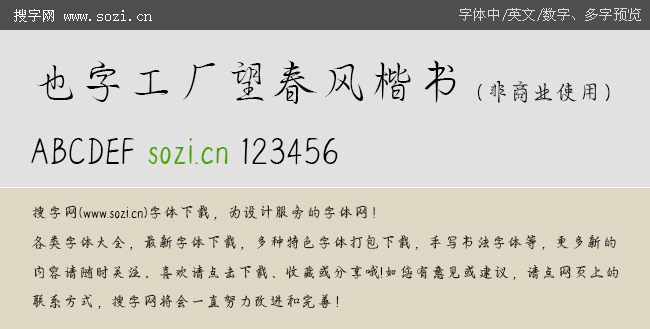
也字工廠望春風(fēng)楷書(shū)
搜字網(wǎng)給大家提供一款也字工廠望春風(fēng)楷書(shū)(非商業(yè)使用)中文字體下載,也字工廠望春風(fēng)楷書(shū)是一款手寫(xiě)字體,字體書(shū)寫(xiě)自然,流暢大方,比例協(xié)調(diào)。適合應(yīng)用于繪本、海報(bào)、書(shū)籍及網(wǎng)頁(yè)設(shè)計(jì)等應(yīng)用(此字體為個(gè)人非商用版,商用可以聯(lián)系:官方網(wǎng)址:https://yefont.com/home,聯(lián)系方式:13798980448)。